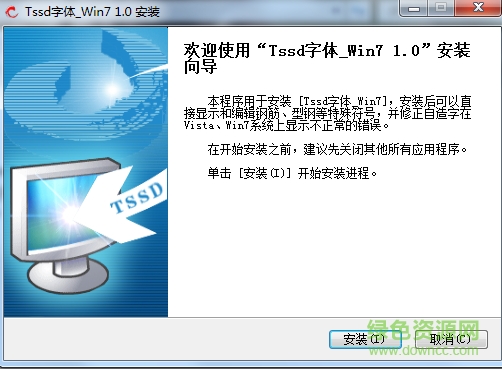
Tssd探索者字體是由北京探索者科技推出的一款cad字體包,支持xp/win7等系統(tǒng),大家找的tssd rein字體也有喲,完全免費使用,適用于需要有鋼筋符號顯示的人員安裝,需要的趕緊下載吧。
探索者系列軟件在CAD上面的應(yīng)用非常廣泛,但是可用的字體卻很少。探索者文字字體是探索者自主開發(fā)的字體文件程序,包含了鋼筋符號、結(jié)構(gòu)符號等特殊符號的文字。不但應(yīng)用于探索者用戶,也可以用于任何文字輸入程序。